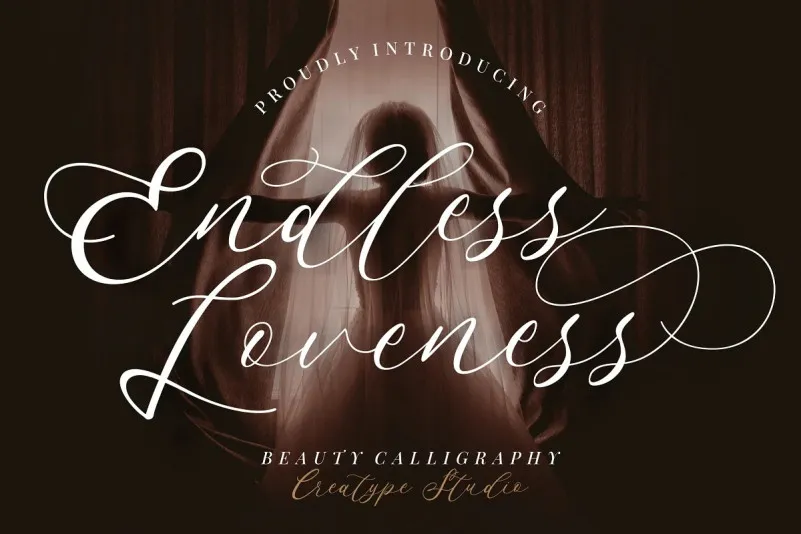
A ‘Endless Loveness Font’ é uma tipografia script que traz alternativas inovadoras às letras padrão, com influências de escrita chinesa e letra a mão. Essa fonte se assemelha à chamadaço ao estilo de desenho à mão, oferecendo uma abordagem única para incorporar em projetos variados. Perfeita para identidade visual, logotipos, designs de casamento, publicações nas redes sociais, anúncios, embalagens de produtos, design de produto, selos, fotografia e até mesmo marcas e material gráfico personalizado. Seja para adicionar um toque delicado a suas criações digitais ou para entregar uma mensagem autêntica em materiais impressos, a ‘Endless Loveness Font’ é sua escolha perfeita. Construída com atenção aos detalhes e intenção de oferecer flexibilidade criativa sem sacrificar qualidade, essa fonte é ideal tanto para iniciantes quanto para profissionais. Ela permite que você se expresse de maneira única em qualquer projeto que precise de um toque delicado de escrita à mão.